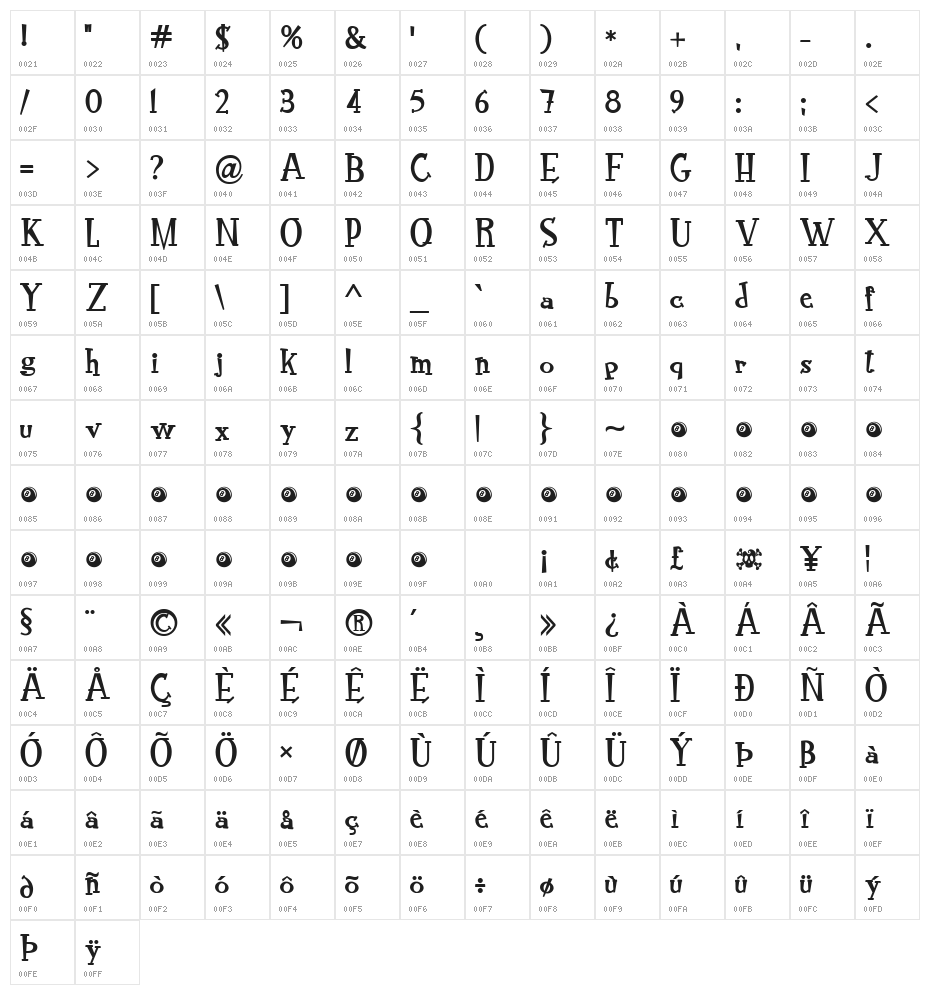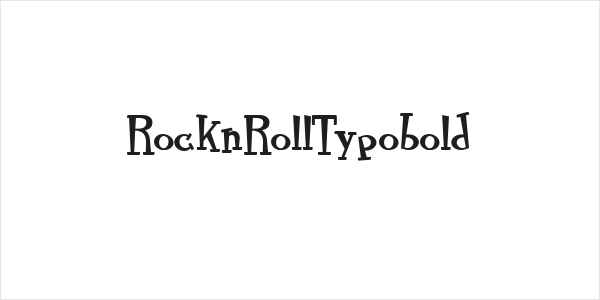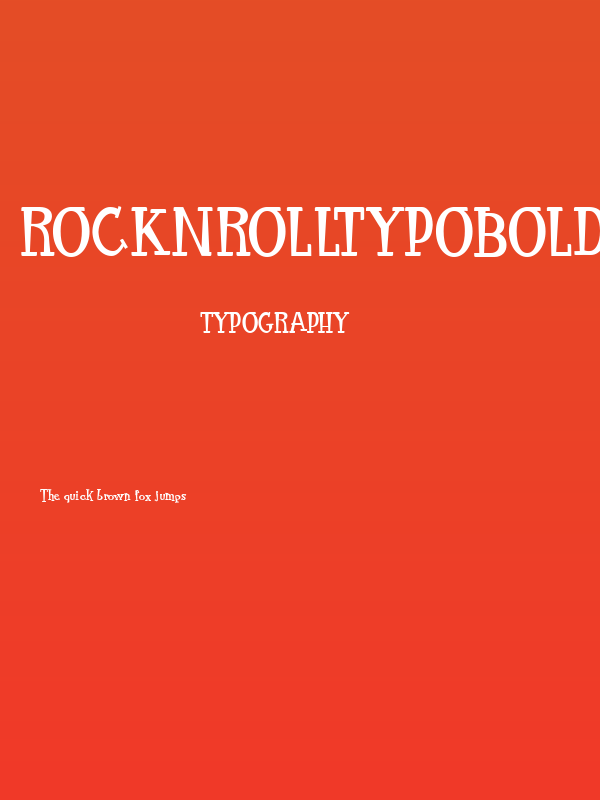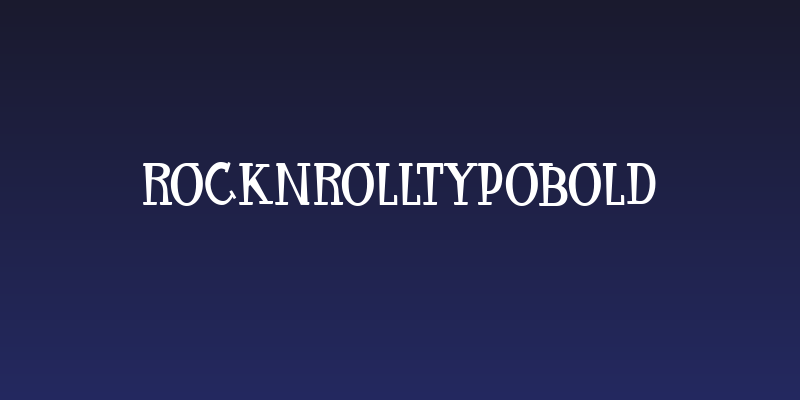
RocknRollTypobold Font
| Progetti proposti | Ideal for music posters, event flyers, branding for creative industries, and any project needing a lively and bold typeface. |